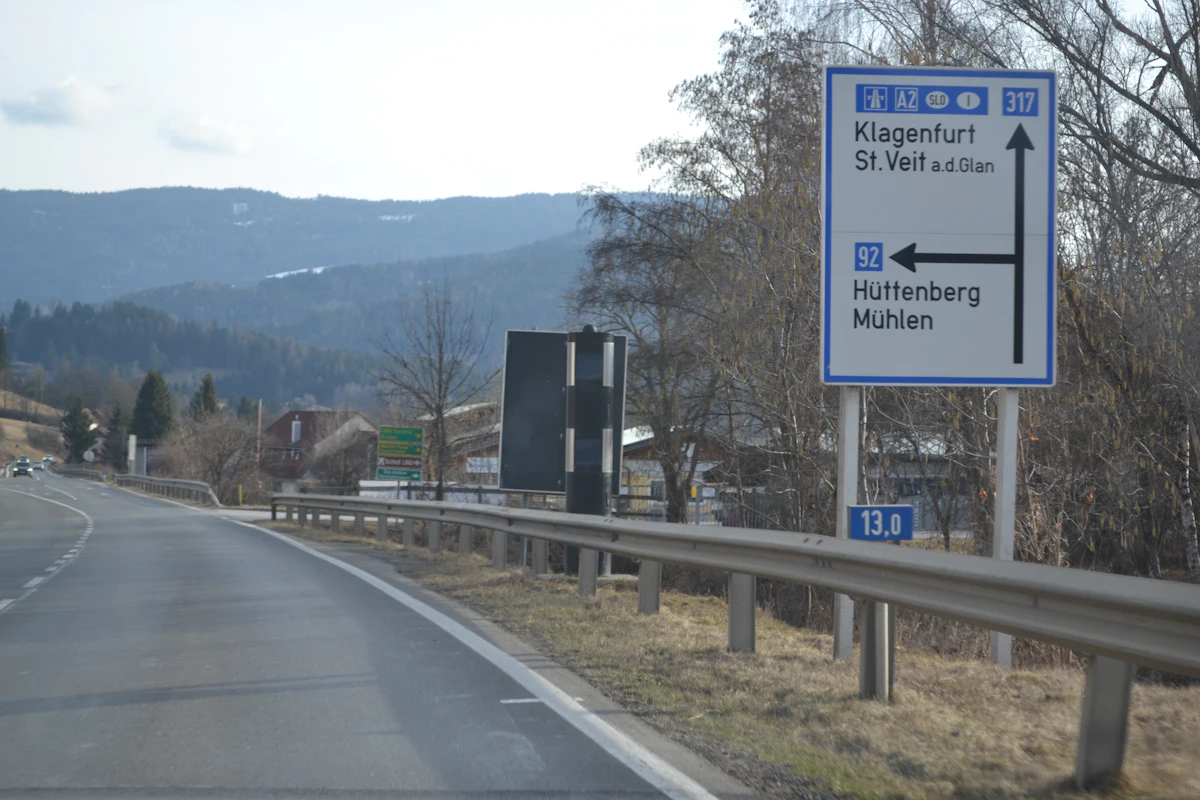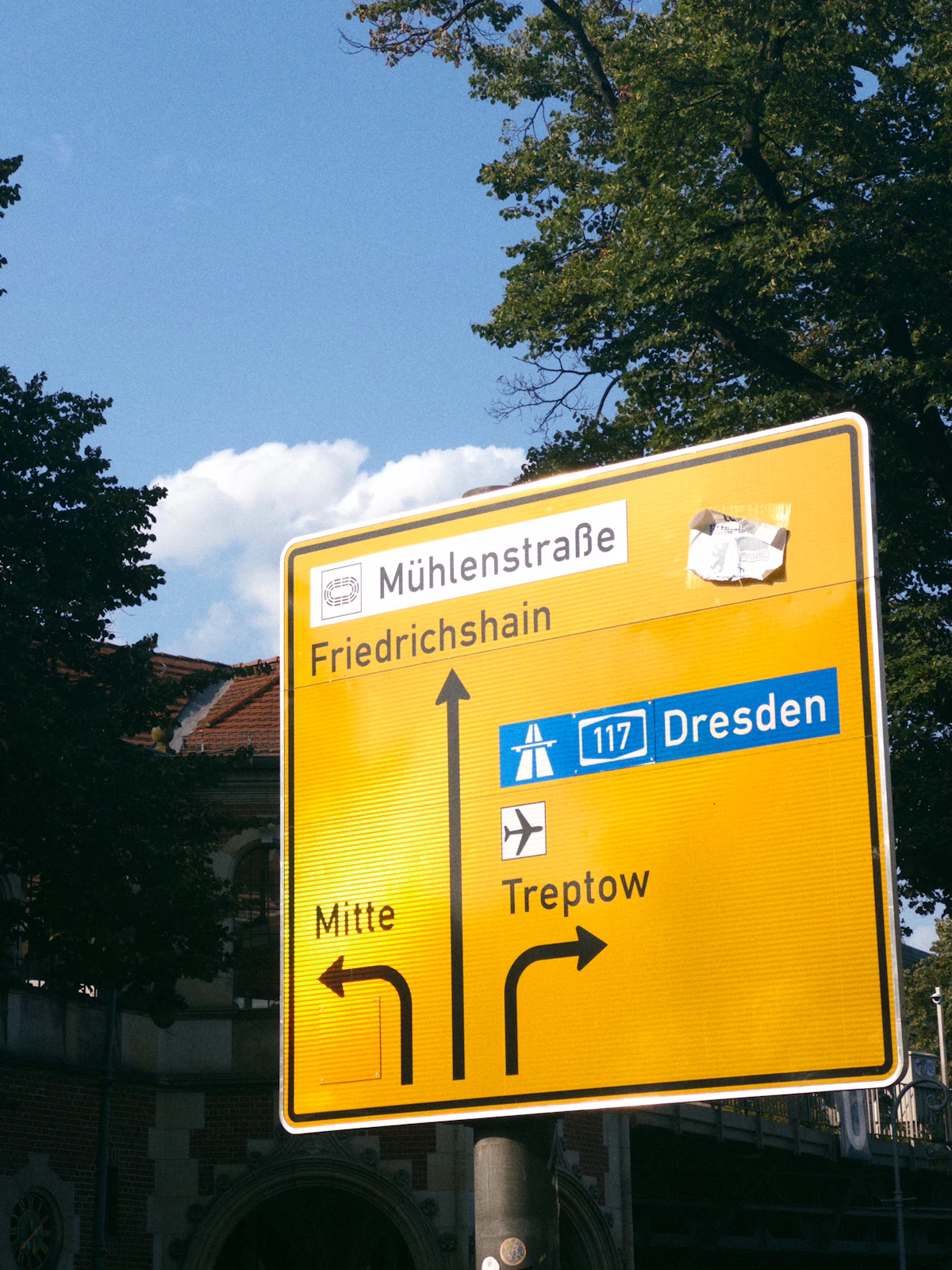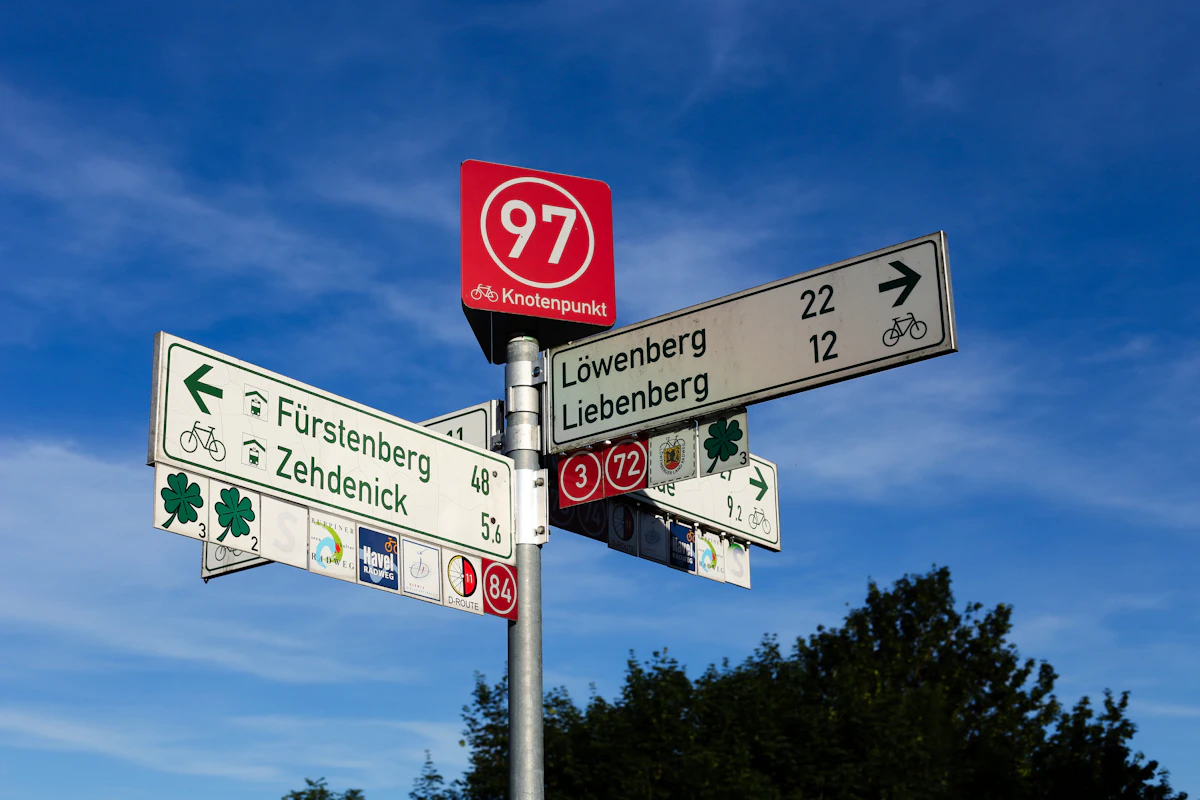
บนทางหลวงในเยอรมนี ป้ายบอกทางวิ่งผ่านสายตาด้วยความเร็วร้อยกว่ากิโลเมตรต่อชั่วโมง ตัวอักษรบนป้ายไม่ได้สวยจนต้องหยุดมอง แต่มันทำสิ่งที่ยากกว่านั้น คืออ่านออกได้ในเสี้ยววินาที โดยที่คนขับแทบไม่รู้ตัวว่าได้อ่าน
ตัวอักษรชุดนั้นชื่อ DIN และมันไม่ได้ถูกออกแบบโดยนักออกแบบตัวอักษร จุดเริ่มต้นของ DIN อยู่ในโลกของวิศวกรรม ไม่ใช่โลกของกราฟิก ซึ่งเป็นสิ่งที่ทำให้มันต่างจากฟอนต์อื่นตั้งแต่ต้น
ป้ายบอกทางสีเหลืองในเยอรมนีชี้ไปเมืองเดรสเดน ใช้ตัวอักษรตระกูล DIN
เรื่องราวย้อนไปถึงปี 1905 เมื่อการรถไฟปรัสเซียต้องการระบบตัวอักษรมาตรฐานสำหรับเขียนบนตู้สินค้า เพื่อให้ทุกคนเขียนเหมือนกันและอ่านออกเหมือนกัน ต่อมาในยุค 1920 บริษัทอุตสาหกรรมเยอรมันมารวมตัวกันเพื่อตกลงมาตรฐานทางเทคนิคหลายอย่าง รวมถึงตัวอักษร ผลที่ได้ถูกเรียกว่า DIN 1451 และประกาศใช้เป็นมาตรฐานในปี 1936
DIN ย่อมาจากชื่อสถาบันมาตรฐานเยอรมัน เป้าหมายของมันชัดเจนและไม่โรแมนติกเลย คือตัวอักษรที่อ่านง่าย แยกแยะได้แม้ในระยะไกล และเขียนซ้ำได้เหมือนกันทุกครั้ง มันถูกสร้างบนระบบกริดง่ายๆ ด้วยเส้นที่หนาสม่ำเสมอตลอด ไม่มีลวดลาย ไม่มีอารมณ์ จากนั้นมันก็ไปอยู่บนป้ายจราจร ป้ายชื่อถนน เลขบ้าน และทะเบียนรถทั่วประเทศ
ป้ายบอกทางบนถนนในยุโรปที่ใช้ตัวอักษรแบบ DIN อ่านง่ายในระยะไกล
สิ่งที่น่าสังเกตคือเหตุผลที่ทำให้ DIN ถูกมองข้ามในตอนแรก กลับเป็นเหตุผลเดียวกับที่ทำให้นักออกแบบหลงรักมันในภายหลัง ความที่มันไม่พยายามเป็นอะไร ความที่มันถูกวาดด้วยตรรกะของวิศวกรไม่ใช่รสนิยมของศิลปิน ทำให้มันมีความจริงใจแบบที่ฟอนต์ตั้งใจสวยให้ไม่ได้ มันดูเหมือนของที่ถูกผลิตขึ้นเพราะจำเป็น ไม่ใช่เพราะอยากอวด
จุดเปลี่ยนมาถึงในปี 1995 เมื่อ Albert-Jan Pool นักออกแบบตัวอักษร หยิบ DIN 1451 มาศึกษาอย่างละเอียดและพัฒนาเป็น FF DIN ฉบับที่ใช้งานในงานพิมพ์และดิจิทัลได้จริง มีน้ำหนักหลายระดับ มีรายละเอียดที่ปรับให้นุ่มขึ้นโดยไม่ทิ้งความเป็นวิศวกรรม FF DIN ประสบความสำเร็จทันที สถาปนิก บริษัทเทคโนโลยี และนักออกแบบกราฟิกพากันใช้มัน เพราะมันให้ความรู้สึกแม่นยำและจริงจังโดยไม่แข็งทื่อ
ป้ายถนนบนเสาตัดกับท้องฟ้าสีคราม ตัวอักษรเส้นหนาสม่ำเสมอแบบ DIN
นับจากนั้น DIN ก็โผล่ไปในที่ที่ไกลจากป้ายถนนมาก ทั้งบนปกหนังสือ บนแพ็กเกจวิสกี้ บนหน้าจอแอป และในงาน identity ของแบรนด์ที่อยากดูสะอาดและมีระเบียบ ที่น่าสังเกตคือมันพาความรู้สึกของป้ายจราจรเยอรมันติดตัวไปด้วยเสมอ คือความรู้สึกว่าอ่านได้ เชื่อถือได้ และไม่ต้องตีความ
เรื่องของ DIN ชวนให้นึกถึงตัวอักษรอีกตัวที่เกิดมาเพื่อระบบ อย่าง ฟอนต์ Johnston ที่ออกแบบให้รถไฟใต้ดินลอนดอน ทั้งสองตัวเกิดจากความจำเป็นในการนำทางคน ไม่ใช่จากความต้องการสร้างงานศิลปะ แต่กลับกลายเป็นงานออกแบบที่อยู่ยาวนานที่สุด
บางทีตัวอักษรที่ออกแบบมาเพื่อให้ลืมตัวมันเอง คือตัวอักษรที่เราจดจำได้นานที่สุด และคำถามที่เหลืออยู่คือ ของที่ดีที่สุดในชีวิตประจำวัน อาจเป็นของที่ถูกออกแบบมาอย่างดีจนเราไม่เคยทันสังเกตมันเลย